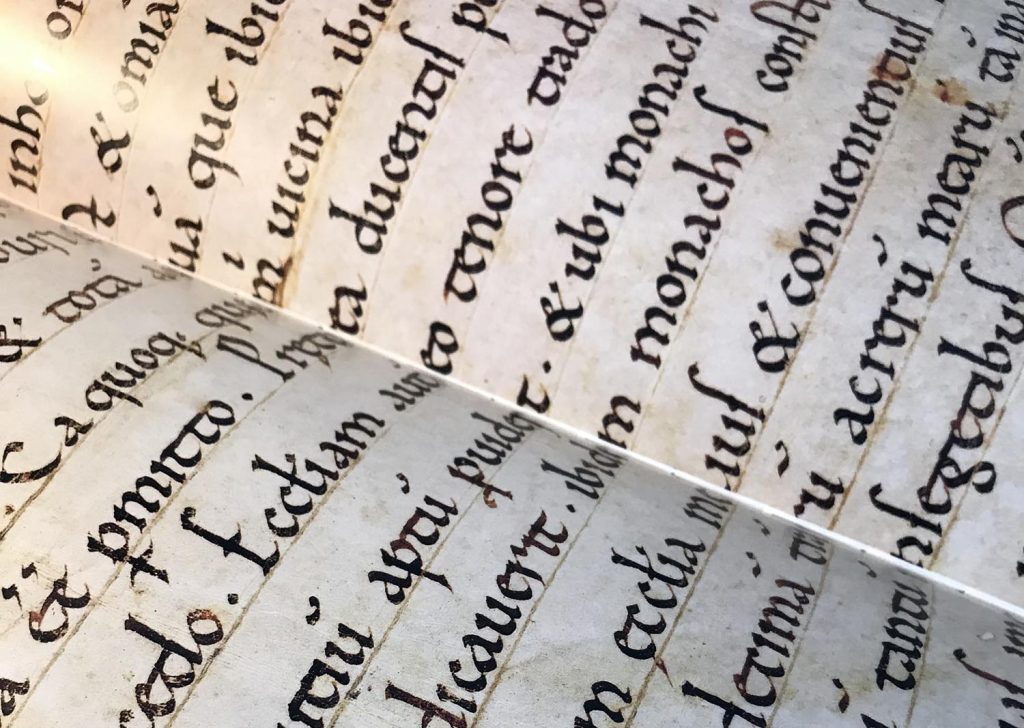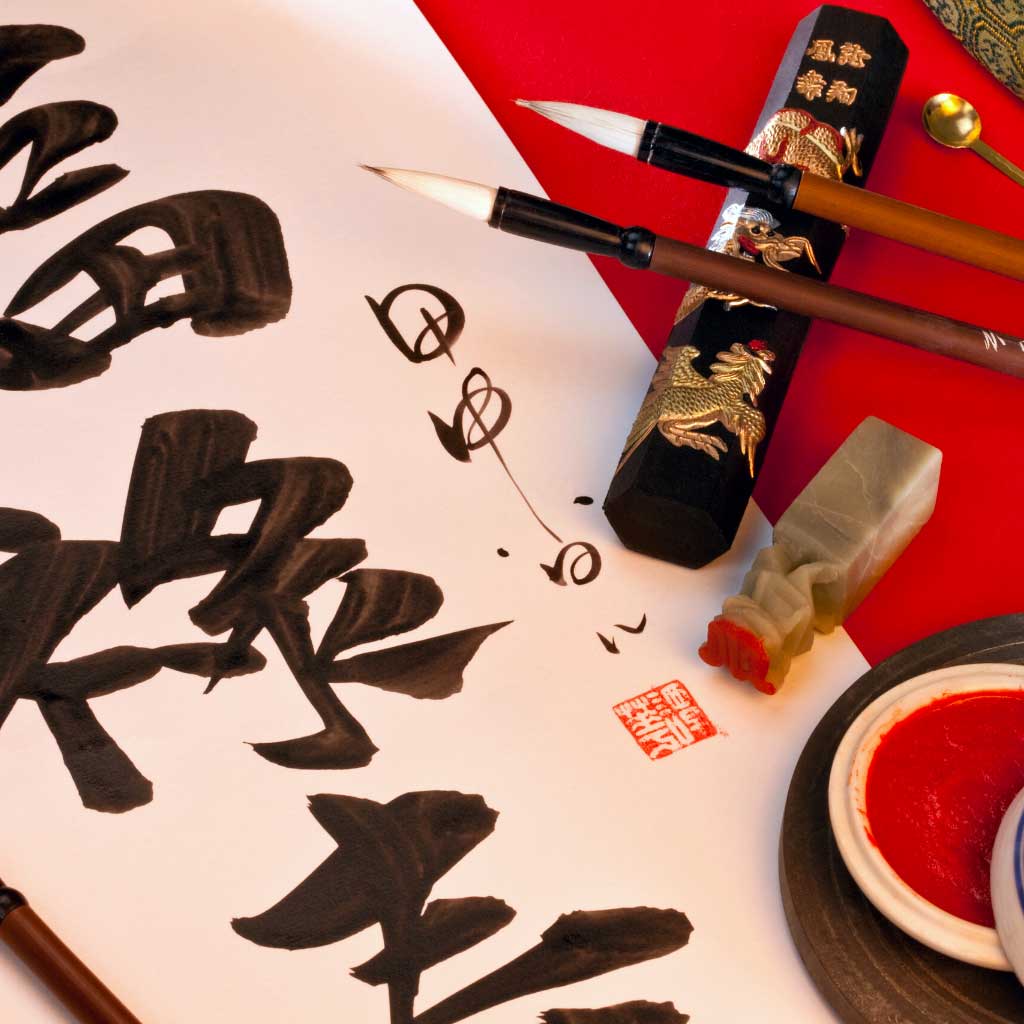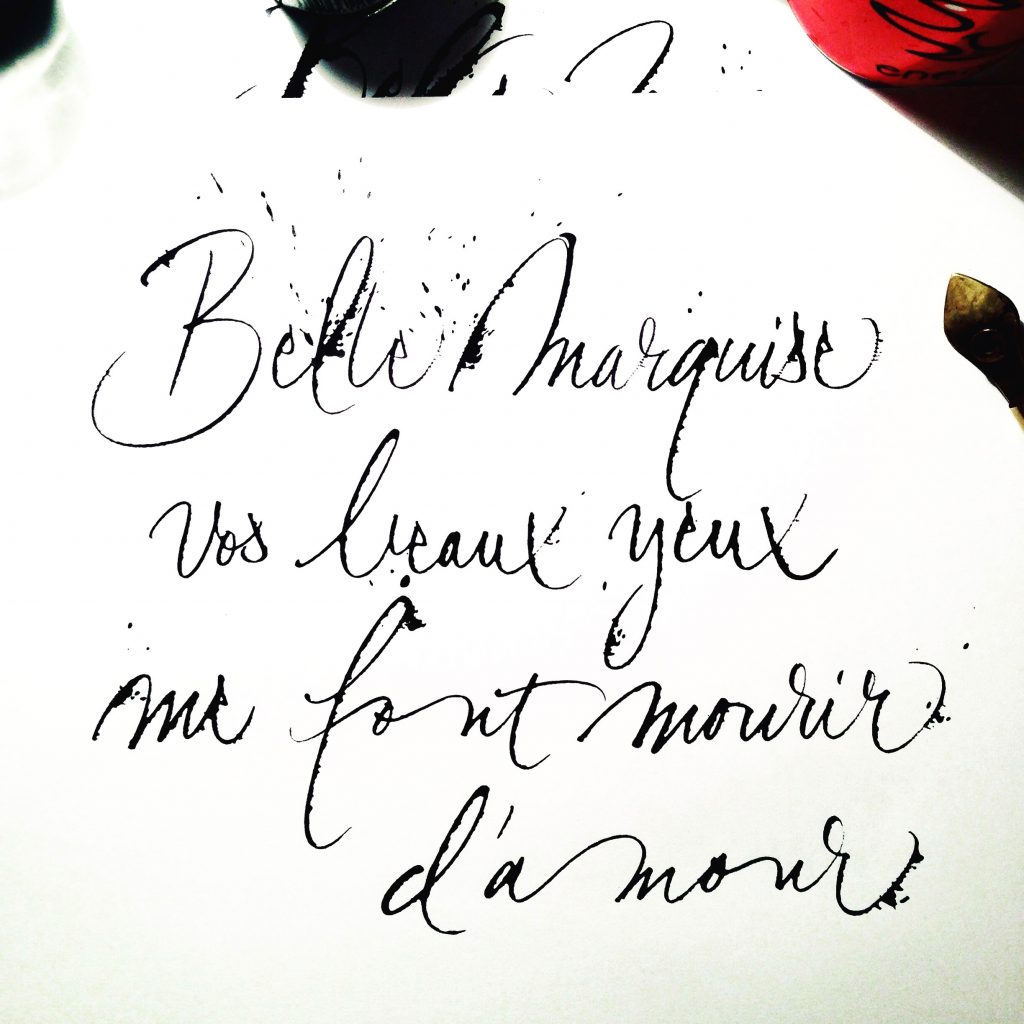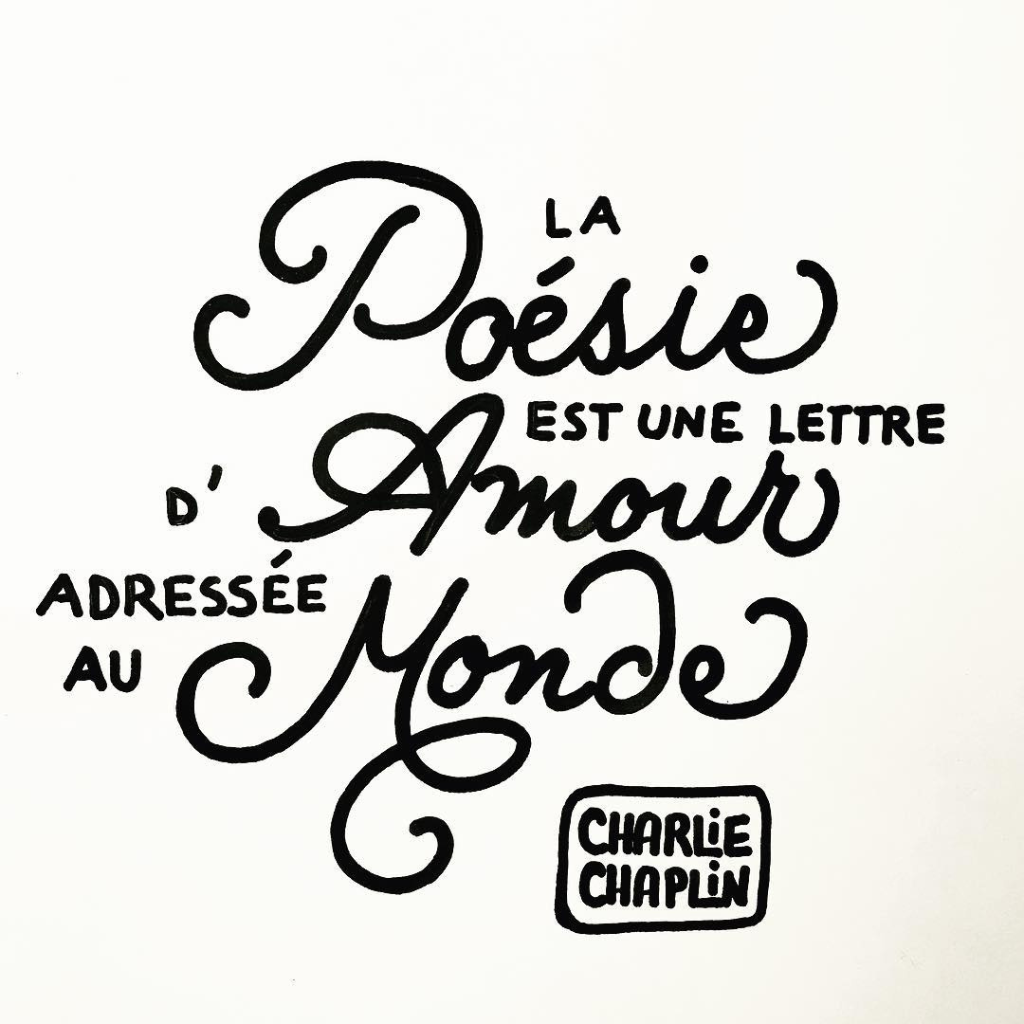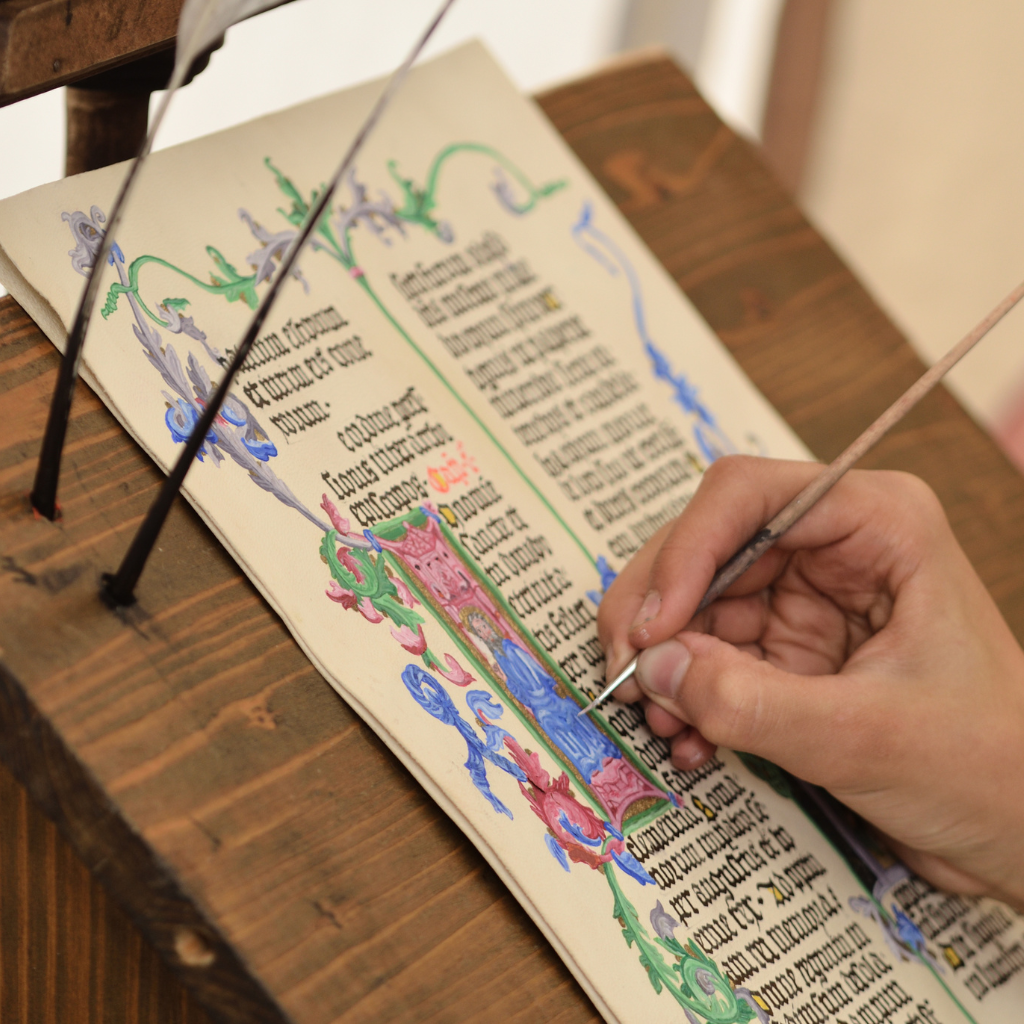
Souvent, lorsque je dis que  je fais de la calligraphie, on me regarde avec des yeux interrogateurs. Je me rends compte que peu de gens connaissent cette discipline ou en ont une image erronée. Quelque chose un peu entre art médiéval  et calligraphie chinoise… bon, vous imaginez…
La calligraphie existe dans toutes les civilisations qui ont une culture écrite. A l’échelle de l’humanité, donc, les écritures médiévales représentent donc une toute petite niche de cet art universel.
Pour faire simple, comment définir la calligraphie ?
Etymologiquement, le mot provient du grec κάλλος (kállos, « beau ») et γραφεĩν (grapheîn, « écrire » : c’est l’art de bien écrire. Mais s’en tenir à l’étymologie occulterait toute l’essence et le sens de la calligraphie.
Prenons un exemple :
Quand je repeins ma salle de bain, je fais de la peinture. Quand je fais une petite carte à l’aquarelle pour ma maman, je fais aussi de la peinture, mais avant tout je produis intentionnellement une « œuvre ».
En fait pour comprendre la différence entre « bien écrire » et faire de la calligraphie, il faut juste se pencher sur l’intention (je veux exprimer quelque chose, je veux tracer de belles lettres) et le résultat (j’ai produit une œuvre).
La typographie
L’écriture est le moyen d’expression, de communication, de traduction et de fixation de la pensée. Elle a été standardisée dans un souci pratique, le paroxysme étant la typographie, qui consiste à créer des caractères à des fins de composition et d’impression.
Pourtant, de tout temps, l’homme a joué avec l’écriture, l’a parée, déformée, embellie :
• En témoignent les magnifiques lettrines que l’on trouve dans les manuscrits anciens.
• En témoigne aussi le foisonnement graphique des lettrages anciens (ou « Vintage »)
La calligraphie met en scène l’écriture, la révèle de façon esthétique. c’est un art vivant, global, en perpétuel mouvement.
La dimension spirituelle
Les asiatiques considèrent la calligraphie bien au-delà du geste, de la représentation et de la production. Ils la voient comme une discipline globale et spirituelle, un art martial, la voie de l’écriture, qui comprend :
• L’ouverture sur le monde
• La connaissance de soi
• La maîtrise du geste
• Les 4 trésors du calligraphe : le pinceau, le papier, l’encre et la pierre à encre.
Plus vous avancerez en calligraphie, plus vous explorerez sans doute cette dimension « spirituelle » et méditative.
La Calligraphie Latine : les écritures originelles
On comprendra ici les écritures occidentales, de l’alphabet latin, qui ont évolué jusqu’à donner notre écriture courante actuelle. Au départ, un signe : l’écriture cunéiforme, qui a évolué vers la cursive romaine. Parmi les écritures historiques, citons par exemple la capitale romaine, les onciales, les carolines, les gothiques, les bâtardes, la chancelière et l’anglaise.
Les écritures historiques s’appuient sur des règles très strictes : c’est le « ductus » qui est la séquence d’exécution des traits pour produire une lettre. Il existe de nombreuses variantes régionales de ces écritures, notamment pour les Gothiques et les Batârdes.
Manuscrit en Caroline
Les outils privilégiés de la calligraphie historique sont la plume d’oiseau, le calame en bambou, la plume métallique en biseau, carrée ou pointue. Les supports sont principalement le parchemin et le papier.
Enfin, la paléographie est l’étude des écritures anciennes.
La Calligraphie aujourd’hui
La calligraphie contemporaine, ou « renouveau calligraphique »
La calligraphie contemporaine qualifie généralement les œuvres produites à partir du XXème siècle, qui s’affranchissent du carcan formel de la calligraphie historique pour aller davantage explorer l’expressivité du trait, toujours dans une optique d’esthétisme et de beauté.
L’expression peut allez jusqu’à des représentations abstraites. L’écriture est dite « gestuelle », en prolongement du corps – et de l’esprit – du calligraphe.
Les outils sont variés voire infinis puisque l’idée est d’explorer aussi tous les champs possibles : plumes, pinceaux, calames, automatic pen, ruling pen, cola-pen, light-graph…
Gestuelle au tire-ligne
Mais il ne faut pas s’y tromper, les grands maîtres de la gestuelle contemporaine sont avant tout des calligraphes chevronnés qui ont une parfaite maîtrise des écritures originelles.
La calligraphie moderne
On entend souvent parler de calligraphie « moderne ». J’avoue que je ne sais pas trop quoi en penser, si ce n’est que tout ce qui n’est pas « historique » est par essence moderne.
On y trouve principalement sous cette appellation des cursives issues de l’Anglaise, souvent exécutées avec des feutres pinceaux (Brush Pen) ou des plumes pointues. Contrairement aux calligraphies contemporaines citées plus haut, les calligraphies dites « modernes » bien que parfois « gestuelles » sont généralement très lisibles. Elles sont abondamment utilisées dans la communication évènementielle.